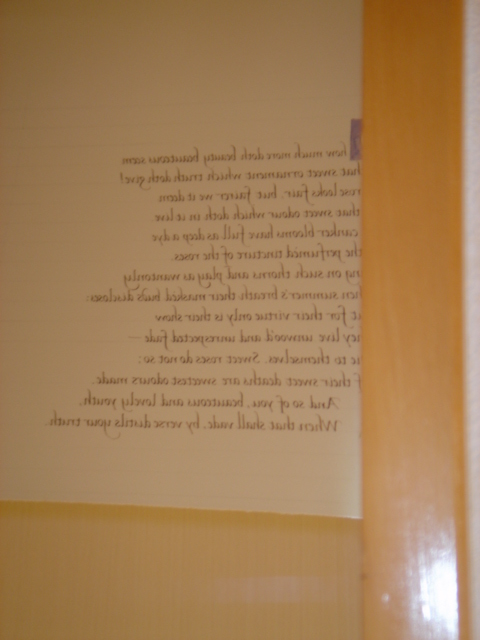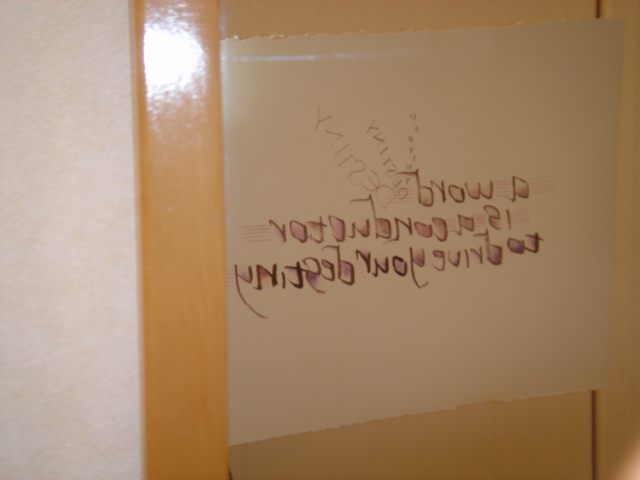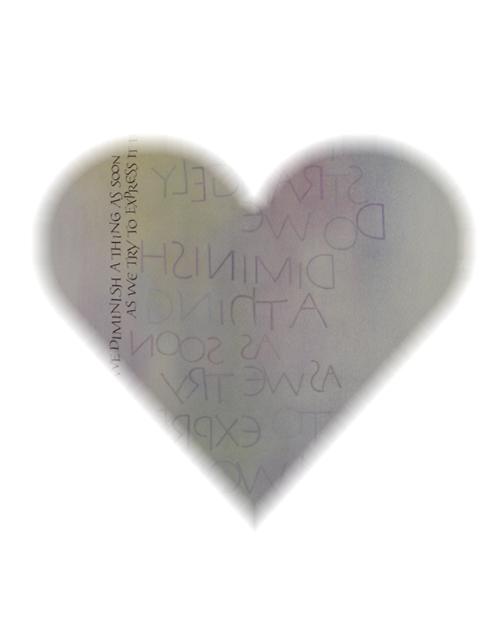
鏡よ、鏡
「fさん、まばたきが多いですね」
へ?
と、これは写真屋さんに言われたのでもなく、目医者さんにでもありません。
以前に声楽の練習で、アシスタントの先生に指摘されたのです。歌っているときのまばたきは禁止!
そうですかあ?自分ではわからないんですけど…と、ブツブツ言ってみたものの、そんなクセなら直すしかありません。
家に帰ってから鏡を見てみる…まばたき、ねえ。
鏡をじいっと見つめながら歌ってみる。すると、その姿にどうしても笑えてきます。
なんじゃ、このヒト、アホみたい…
しかし、自分を客観視できるのも鏡のおかげです。外出時、ウインドーなどに映る姿に現実を突きつけられてビックリしますけど。
もし、鏡がなかったら、どんな生活かしら?
すごい格好してるんだろうな、フフ。池とか水に姿を映しに行くのかも
さて、文字書きさんたちにも鏡は有効です。
自分の書いたものを他人の目で見るのはなかなか難しいものです。親切な他人さんが見てくれればいいのですが、一人っきりのときは鏡に映して見るとよいですよ、とアドバイスされましたっけ。悩めるあなたに鏡が答えをくれるかも!
でも、こうやって裏返しの文字を見ると大抵ヘンに見える…ので、みんなボツになっちゃったとさ。書き直しね!
他に、紙を天地ひっくり返して見るというのも他人の目になれて、よい方法ですよ。
最初から裏返したように書いた文字はどうなのよ?
(こわくて鏡に映す勇気がないんですけど…)
これはモノラインなので、普通に書けましたが、
鏡文字を書いたダ・ヴィンチさま!尊敬いたします。
ケナフ・クロッキー用紙
練習用紙はいつでも悩みの種です。滲まず、ひっかかりすぎず、高価でなく、いろいろなサイズが揃っていて、下が透けて見えて、1冊になっているもの。
そうなるとかなり範囲は狭まってしまうのです。
通常使っているTOOのレイアウトパッドは、お値段以外はまったく問題ないのです。でも練習用紙なのに1枚20円近くするというこの事実。くしゃくしゃポイはできません・・・!
これではコピー用紙でついつい練習したくなってしまいますよね・・・。
そんな時、はるか西方より良き知らせ有り。
神戸のH子さんが発見したケナフのクロッキー用紙。ミューズさんから出ています。
試しに送ってくれたので書いてみました。
これは! 以外と! い・け・る・かも〜!
でもわたしがもらったのは、F6というサイズざんした。
A3よりも横が広く縦が短い感じでしょうか。
スパイラルで綴じてあるので、はがすときにビロビロになりますが、カッターで切ってしまえば大丈夫。H子さんは教室でこれを使っていくかも、とのことです。
すべりもよいし、ひっかかりも多少あるので書きやすいです。
どうぞお試し下さいまし。
ちなみにちゃーんとAcid Freeなので、いいですよね
ヨガとカリグラフィー
ご無沙汰致しておりました。
自分から名乗るのもなんですが…私…ポッチンでございます。
はいはい、ご主人さまのPCが天に召されまして…私も喪にふくしておりました。今もお暇を頂いているところでございますが、
何やらご主人さまにお付き合いということで…。
ご主人さまは、通われる製本教室で、先生が太極拳の話しをしてく
ださるので…いつか太極拳と製本がコラボするのか…と淡い期待をしておられるそうでございます…。
それならばと…ご主人さまが最近購入したのは、ヨガマットです。
…お金がなくてヨガスタジオに通えないご様子、でも
自宅でDVDを見ながらヨガができるので、実践されております…。
昔、ボストンで、このマットを抱えてヨガスタジオに通う美しい
女性達を見て、密かにマットに憧れていたとのことで…。
そして、カリ人ならば…ヨガの呼吸法で練習、練習ぅ〜っと〜!
ぇえ〜!?ご主人さま〜?私にデモをしろと…?
さ、さようでございますか…。では、まず呼吸法…吸って〜、吐いて〜、吸って〜、吐いて〜ですが、吸うときはお腹を膨らまし、吐くときはお腹をへこまし…。
「はっ?このお腹が出っ張っているのは…もともとでございますから…まっ、体形には個人差がございますので…気にしない、気にしない…。」
これは本当にご主人さまが、吸って〜、吐いて〜、吸って〜、吐いて〜を繰り返しながら書かれた練習線でございます。道具はルーリングペン?とか申されておりました。
はっ!これは、立ち反りのポーズでございます!私もこのように…ぅ、ぅ、う〜苦しいながらも立っております。この間にも吸って〜吐いて〜を繰り返すのでございます。
吸って〜吐いて〜、呼吸はしながら立ち反りのポーズをイメージしながら練習された線でございます!
はぁ〜、ゆったりとしながらも、きつい動作が繰り返される
ヨガでございますが…、時々身体をほぐさねばなりません。
では、お言葉に甘えまして、私も…脱力〜ふぅ〜ぅ〜ぅ〜。
お恥ずかしいですがぽってりお腹をお見せしております。
ご主人さまは脱力してルリルリ線を練習でございます。
ささっ、皆様、どうぞ、吸って〜、吐いて〜、吸って〜、吐いて〜の呼吸でカリの練習を
してみてはいかがでございますか?
イタリック体の練習
昨日はArrighiに関してバカバカしいことを書いたので、や〜ん、ライティングマスターの神様がへそ曲げちゃったらどうしよう、とちょっと心配になり、そうだ、心も新たに練習しようと思って少し文字を書いてみました。
こういう動きのあるイタリック体の文字を書くときには、ブラウゼのペン先が何と言ってもひっかからずに書きやすいのですが、わざとひっかかるミッチェルで書いたらどうなるかを以前試した事があって、それをもう一度書いてみたのです。
紙もざらざらしているし、ミッチェルは角がシャープでひっかかるし、スピードを早く書く事はとても困難!ガリガリくんです。
でも書き続けて行くと、こんな感じに面白い線が出てきました。
雑にならない様、線の美しさを意識して書くべし、と肝に銘じて練習しますが、なかなかそれはとっても難しい。
どうしても雑になってしまいますよね。ここが練習のしどころ、課題、必須事項です。
でも試してみる価値はありました。文字の種類や書き方によって道具を選ばなければなりませんが、敢えて使いにくい道具でやってみる。そうすると何か新しい発見ができるかもしれませんね。
やはりブラウゼだとひっかかりがなく、とても書きやすいです。(でもあとから見るとなんだかウルサイ感じ。フワフワではなく、うじゃうじゃになってしまった・・・・)
さてさて、美しい文字を書くにはこれからも練習あるのみ!きれいでオーガニックな線を持ち、美しく動きがあり個性が存在するイタリック体を目指しま〜す。
alphabet sentences
文字を練習する時、ひとつの文字のみを練習するのではなく、必ず単語、文章で練習しなければなりません。なぜなら、文字はひとつで書かれる事はほとんどなく、必ずつなげて書くからです。そう、スペーシングの練習をしなければならないからです。
そこで一つの文章でaからzまでを書けるアルファベットセンテンス(pangram)で練習します。The quick brown fox jumps over the lazy dog.は最も有名ですよね。
でも、いつも同じだとつまらないから、いろいろとちがった文章を書こうとしますが、なかなか簡単で覚えやすいのはありません。
しかし、先日パラパラと昔の資料を見ていたら、面白いのを見つけましたよ〜。
The exiled queen, justly moved, celebrates with a dazzling fire work display.
正当にお引越しをして国外追放された女王は、まばゆいばかりの花火の展示でお祝いされます。
He jokingly removed the porcupaine quills from the zebra's back with wax.
彼はシマウマの背中からヤマアラシの大羽根をワックスを使ってふざけて取り除きました。
Six of women quietly gave back prizes to the judge.
6人の女性は静かに賞を審判に返しました。
想像しながら書けば、スラスラと練習出来る事でしょう!さあ、みなさんも、ヤマアラシを思い浮かべて練習練習!